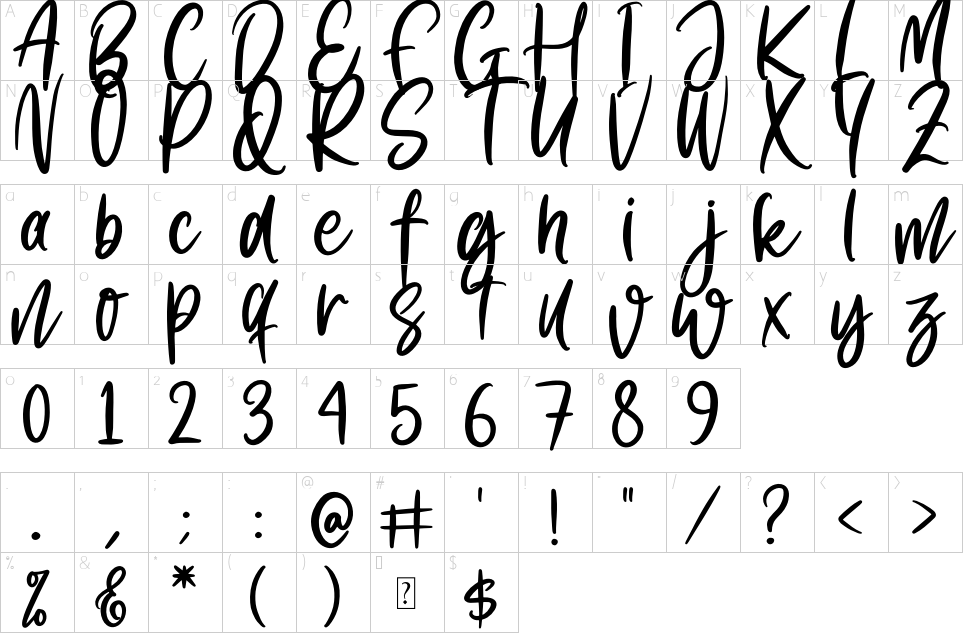
Descubra uma nova fonte de estilo chamativo e colorido chamada Menttari Sparkle, perfeitamente adequada para suas necessidades de design. Desenhada pelo Studio Perspectype, esta fonte gratuita oferece uma maneira única de enfeitar qualquer projeto. Com 832 downloads até o momento, Menttari Sparkle é mais do que uma opção; é uma maneira de se conectar com designers do mundo todo que buscam a perfeição em cada letra. Se você está procurando por algo que dê vida à sua tipografia, Menttari Sparkle é uma fonte que certamente merece sua atenção. Descubra como este design poderoso e colorido pode revolucionar a forma como você visualiza o design em seu próximo projeto.